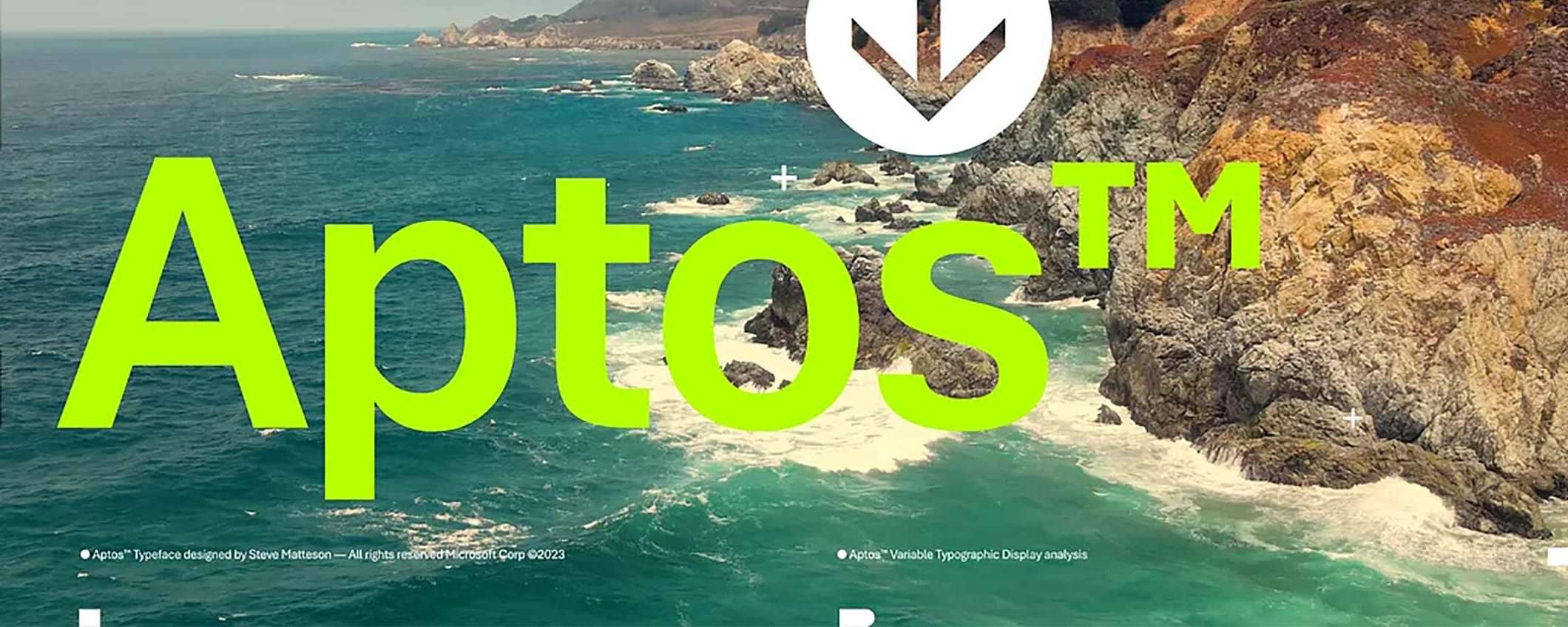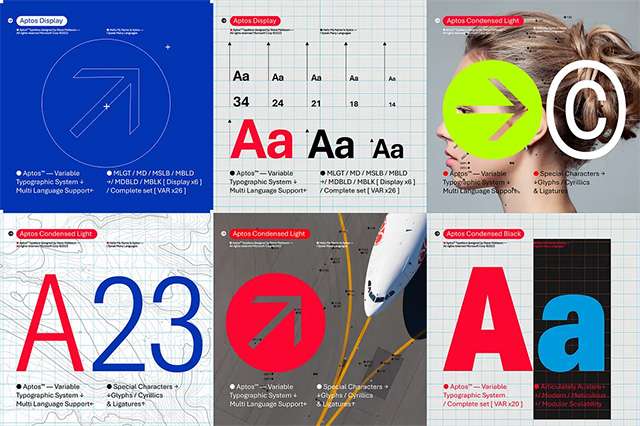
Aptos è il nuovo font di default per Microsoft (addio Calibri)
Aptos è il nuovo font di default per Microsoft
Microsoft ha svelato quello che sarà il suo nuovo font di default: si chiama Aptos (già Bierstadt) e prenderà il posto di Calibri.
Trascorsi 15 anni dall’adozione di Calibri, Microsoft ha scelto quello che sarà il nuovo font di default per il suo intero ecosistema di prodotti, servizi e applicazioni: Aptos. Un cambiamento dettato anzitutto dalla volontà di adattarsi ai nuovi dispositivi in circolazione: La tecnologia che utilizziamo ogni giorno è cambiata e così, abbiamo iniziato la nostra ricerca per il font perfetto per gli schermi in alta risoluzione.
Il nuovo font Microsoft: addio Calibri, c’è Aptos
Il percorso ha avuto inizio nell’aprile 2021, quando la software house ha chiesto ai suoi utenti di votare tra una selezione di cinque font per trovare quello giusto: Bierstadt, Grandview, Seaford, Skeena e Tenorite. A spuntarla è stato il primo del quintetto, Bierstadt, ribattezzato poi Aptos in omaggio a una località della contea di Santa Cruz, in California. A crearlo è stato il designer Steve Matteson già al lavoro in passato sul formato TrueType per Windows e sul ben noto Segoe.
Esempi di utilizzo di Aptos, il nuovo font di default di Microsoft
Di tipo sans serif (senza grazie), Aptos troverà posto anzitutto negli applicativi che compongono la suite Office (ora Microsoft 365) a partire a stretto giro da Word, Outlook, PowerPoint ed Excel. A caratterizzarlo sono l’impiego di forme geometriche, i tratti netti e la capacità di adattarsi alle esigenze di ogni lingua in modo da risultare sempre chiaro e ben comprensibile, a ogni dimensione e su qualsiasi tipologia di supporto, digitale o cartaceo.
Giunge dunque a conclusione l’era di Calibri, introdotto con la distribuzione di Office 2007 con l’obiettivo, all’epoca, di rimpiazzare Times New Roman e di mandare definitivamente in pensione Arial (obiettivo in verità mai raggiunto). Gli altri quattro font citati poc’anzi, ovvero Grandview, Seaford, Skeena e Tenorite, battuti da Bierstadt, saranno comunque selezionabili all’interno degli applicativi del pacchetto Office.